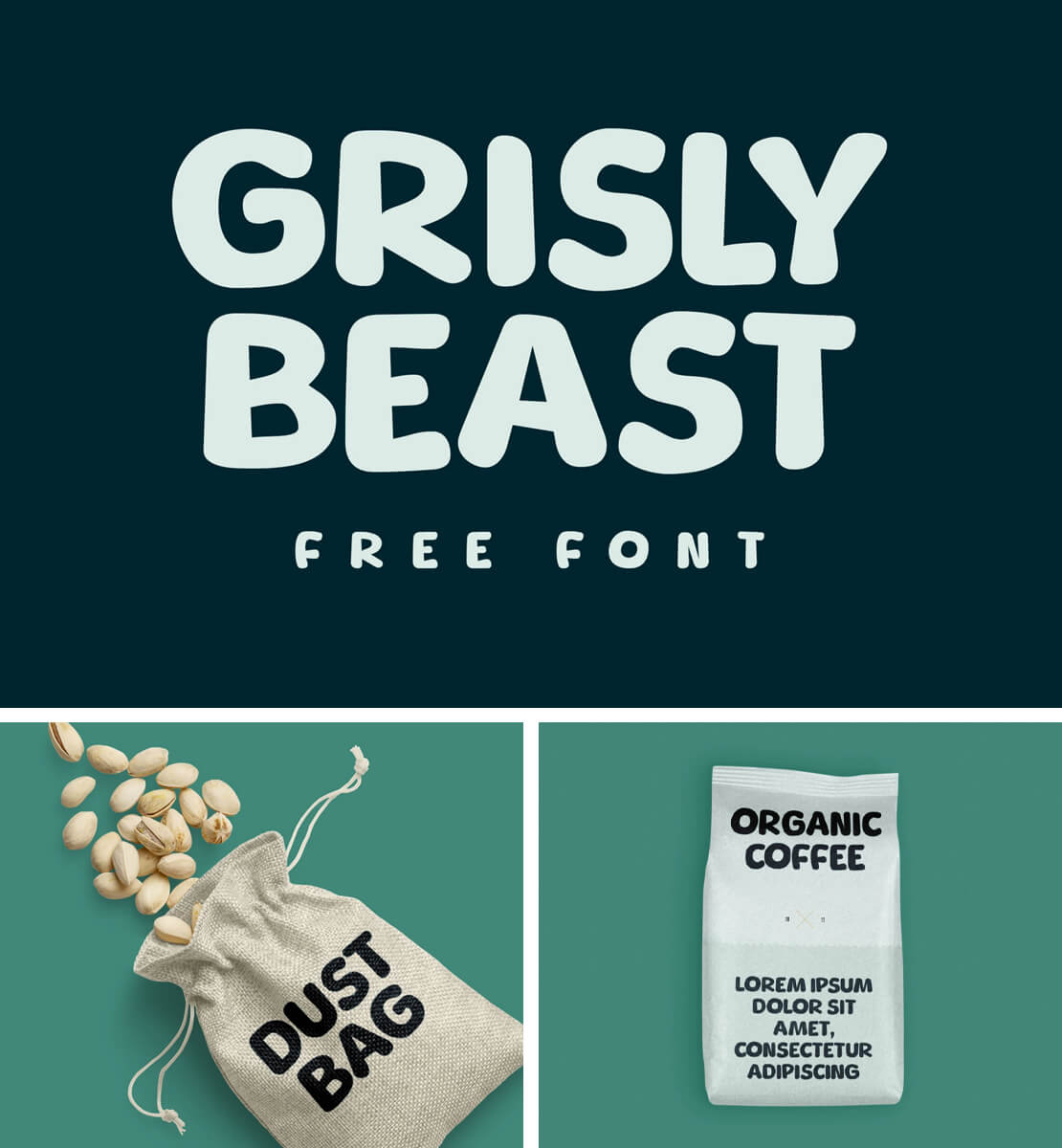
Grisly Beast
Eine kräftige Display-Schrift mit organischer und handgemachter Anmutung. »Grisly Beast« von Niskala Huruf steht für private und kommerzielle Zwecke kostenlos zum Herunterladen bereit.
Das Schriftbild von »Grisly Beast« zeichnet sich durch dicke, abgerundete Buchstaben aus. Durch diese weiche und unregelmäßige Formensprache erhält der Font einen natürlichen, freundlichen und spielerischen Charakter. Das Alphabet ist dabei als reine Versalschrift (All-Caps) angelegt und enthält unter anderem auch deutsche Umlaute.